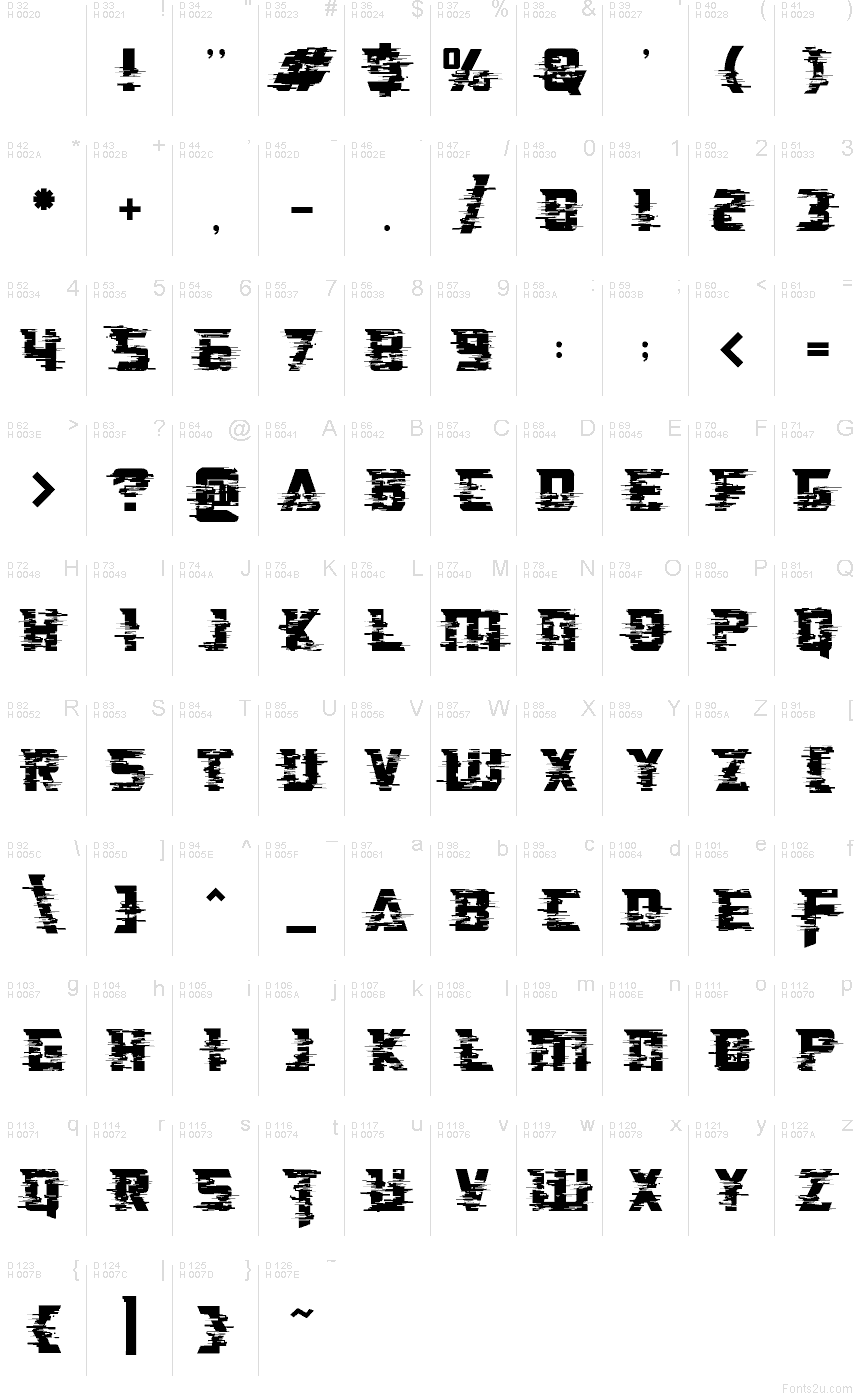
Turbo Type Three od Putracetol Studio je bezplatné glitch techno písmo definované tlustými černými tahy, které jsou opakovaně protínány vodorovnými liniemi. Tato textura poškozeného signálu prostupuje celým designem, takže písmo nepůsobí jen jako obyčejné zkreslení, ale jako televizní obraz, který ztrácí synchronizaci.
Skvěle se hodí pro názvy her, plakáty kybernetických akcí, hudební grafiku, streamovací prvky a sci-fi branding, kde mohou tyto rozbité pásy hrát roli vizuálního vyprávění. Nejvíce vynikne v krátkých nadpisech a logotypu, kde pevné základní tvary udržují údernost, zatímco interference dodává pohyb a napětí.
Turbo Type Three